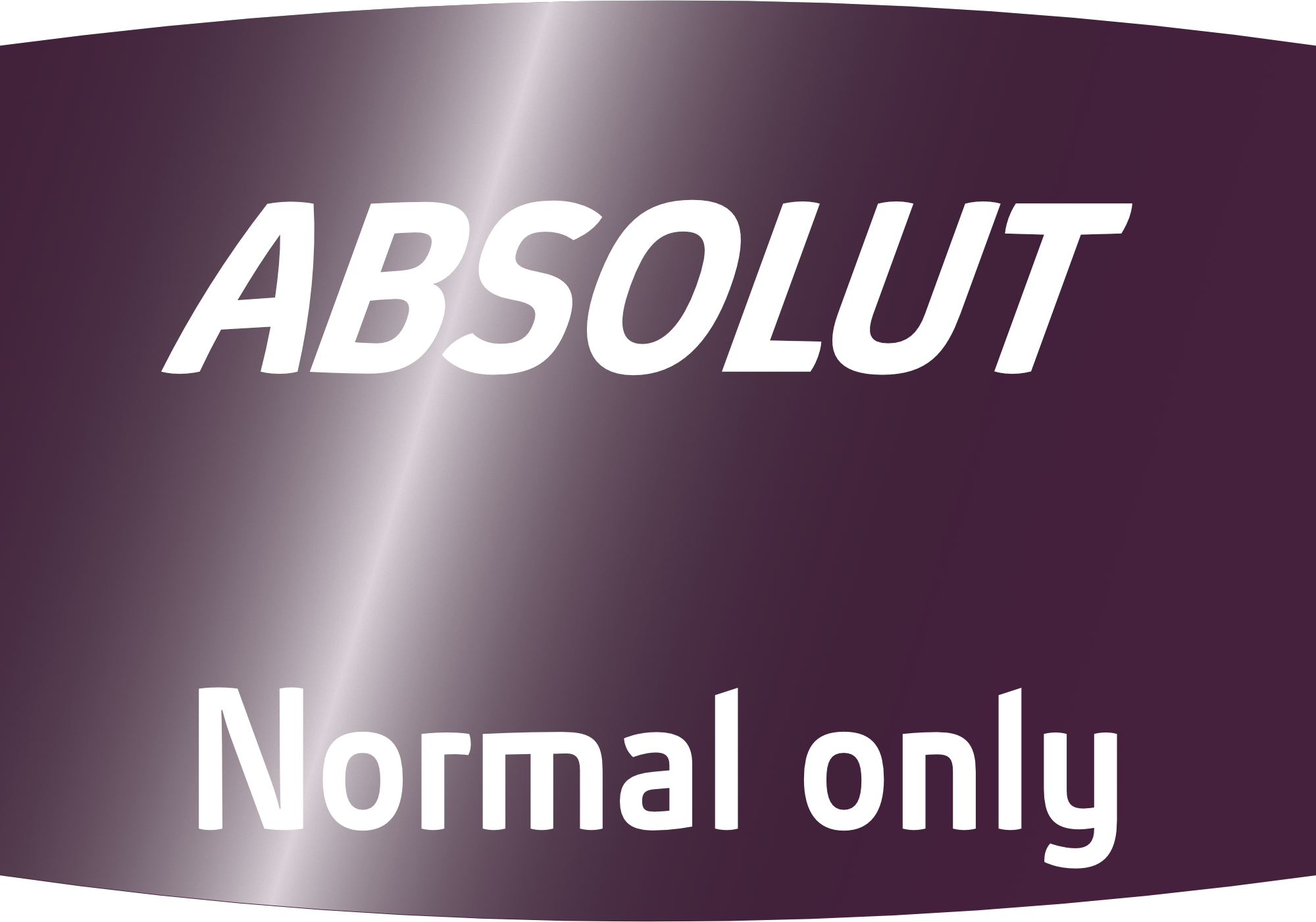
Absolut est la police moderne du nouveau millénaire. Réduit à l’essentiel – police pure : moderne, technique, sans compromis, sobre, esthétique.
Des fonctions supplémentaires peuvent être activées et désactivées en tant que fonctionnalités OpenType :
Lettres alternatives :
remplace les lettres a, g, u par la variante alternative.
Ligatures :
remplace les paires de lettres cc, ck, ff, fi, fl, fj, ft, th, tt, tz, ffi, ffl par la combinaison de lettres respective.
Chiffres de table :
remplace les chiffres normaux par des chiffres de tableau avec des largeurs de caractères identiques.
Fractions :
remplace les combinaisons de caractères 1/2, 1/3, 1/4 etc. par les fractions correspondantes.
Lettres historiques :
remplace s par « long s » et SS ou SZ par un ß majuscule.
Zéro avec une barre :
remplace le chiffre « normal » 0 par la variante avec une barre oblique.
Stile set 1 :
remplace la forme « ronde » de a d'un par la variante « à deux étages ».
Style set 2 :
remplace la forme « ronde » de g par la variante « à deux étages ».
Style set 3 :
remplace la forme « ronde » de u par la variante « cassée ».
Style set 4 :
remplace les nombres normaux (1 à 20) par des nombres dans un cercle.
Stile set 5 :
remplace les nombres normaux (1 à 20) par des nombres négatifs dans un cercle.
Support linguistique :
Unicode Latin 1 (langues d'Europe occidentale et septentrionale) ;
Unicode Latin Extended A (langues d'Europe centrale et orientale, turc) ;
Grec (ISO 8859-1) ;
Le cyrillique ;
Vietnamien